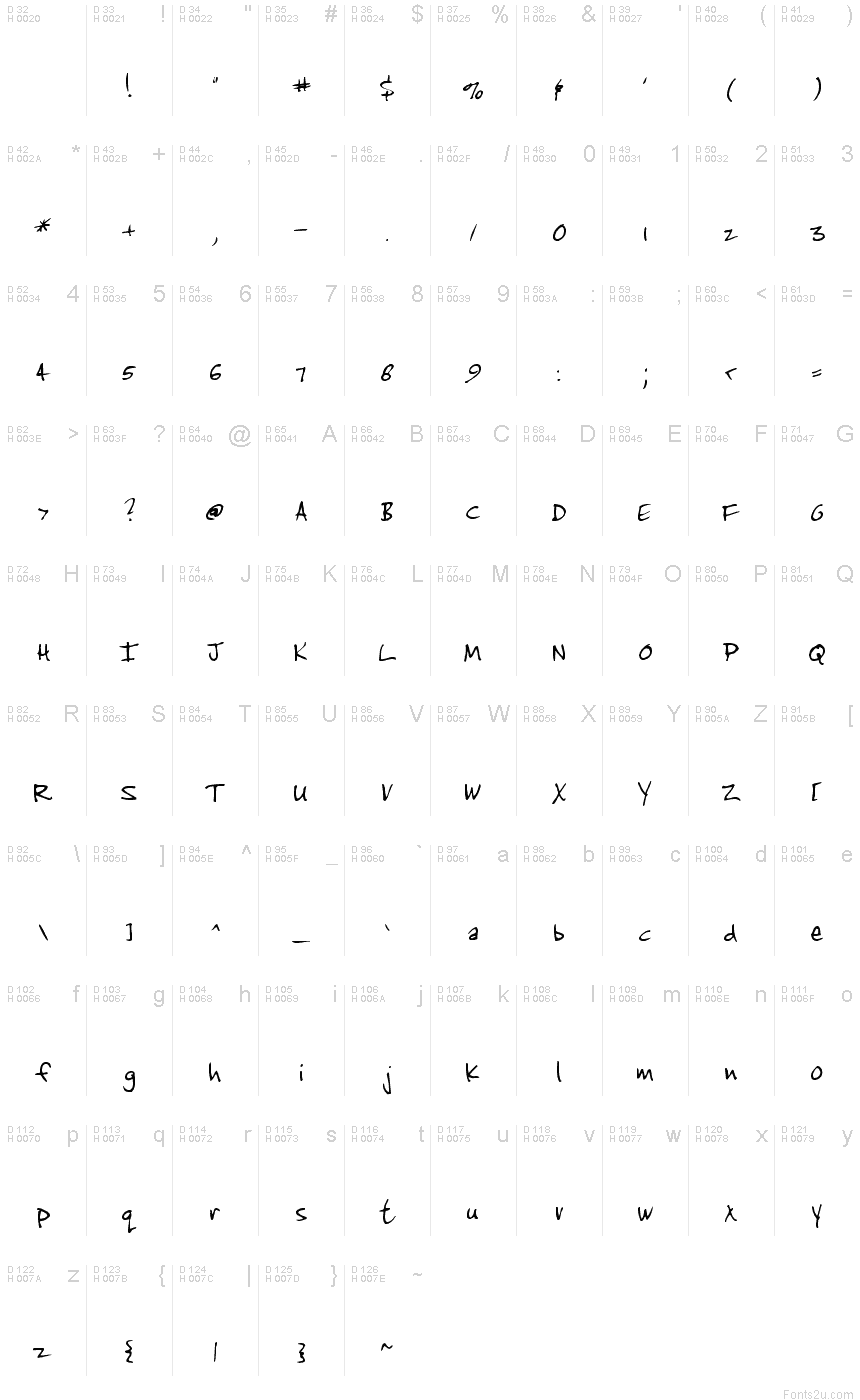
Jenkins v2.0 od Fontalicious Fonts to darmowy, odręczny krój pisma o luźnej, „atramentowej” energii szybkiej notatki nabazgranej na serwetce. Wysokie, lekko pochylone litery i nierówne pociągnięcia sprawiają wrażenie spontanicznych i naturalnych – jakby zostały rzucone na papier markerem, który zostawia nieco rozmazane krawędzie. Rytm jest żwawy, ale zaskakująco czytelny, co nadaje projektom surowy, osobisty charakter, nie wpadając przy tym w chaos.
Używając Jenkins v2.0, nadasz charakter plakatom, zinom, okładkom w stylu szkicownika, miniaturkom na YouTube, niezobowiązującym logotypom, postom w mediach społecznościowych i etykietom produktów handmade. Ten darmowy font świetnie sprawdza się w większych rozmiarach, gdzie jego nierówne krawędzie i zabawna dynamika naprawdę mogą się pokazać. Połącz go z prostym, czystym krojem bezszeryfowym w tekście głównym, aby zachować czytelność układu, podczas gdy nagłówek przejmie całą uwagę.